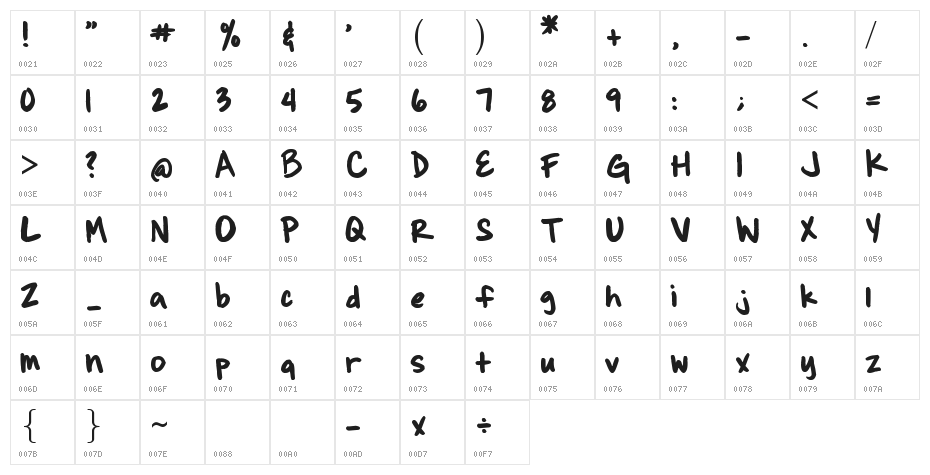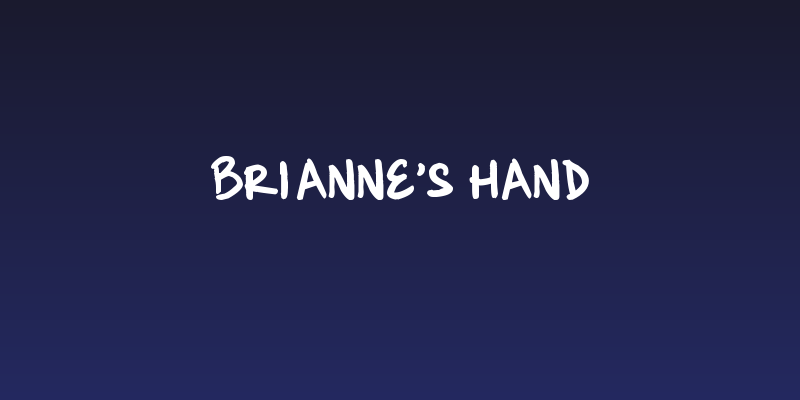
Brianne's hand Font
✎ Handwritten
Fonts by Jeni Hopewell
| 分类 | Handwritten |
| 整体风格 | Casual, Playful |
| 使用场景 | Headlines, Informal text, Creative projects |
| 推荐项目 | Ideal for greeting cards, children's books, personal blogs, and informal branding projects. |